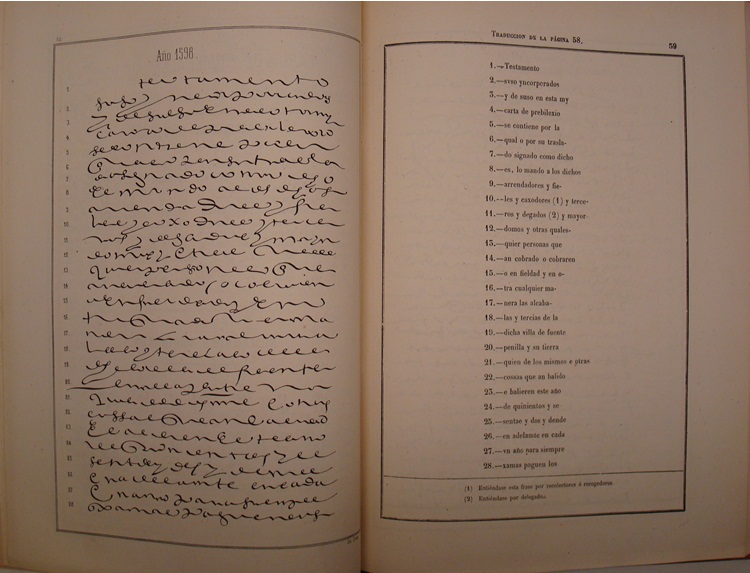
La Historia de la Paleografía en el s. XIX está directamente marcada por la gran obra de finales del XVIII del P. Merino:
"ESCUELA PALEOGRAPHICA ó DE LEER LETRAS ANTIGUAS". (
Madrid: Juan Antonio Lozano, 1780) y la mayoría de autores hacen referencia directa a ella reproduciéndola en sus tratados. Estas obras, junto con la paleografía de Palucie y Cantalozella y las diferentes obras de Muñoz y Rivero de finales del XIX de las cuales ya hemos hablado anteriormente, son las más importantes publicadas en el s XIX en España sobre la materia.
En general todas las obras citadas ayudaron a generalizar y difundir la paleografía en las escuelas de estudios superiores y su edición más utilitaria que lujosa demuestra el cambio en la accesibilidad a la educación de mayor número de alumnos y estudiosos de la paleografía en el s XIX que en anteriores épocas.
Referente al contenido estricto de su validez actual, algunos paleógrafos como C. A. Millares no dan mucha importancia académica, sinó la meramente bibliográfica y histórica a estas obras, excepto a las de Muñoz y Rivero.
ALVERÁ Y DELGRÁS, ANTONIO, "COMPENDIO DE PALEOGRAFÍA ESPAÑOLA ó ESCUELA DE LEER TODAS LAS LETRAS QUE SE HAN USADO EN ESPAÑA DESDE LOS TIEMPOS MÁS REMOTOS HASTA FINES DEL SIGLO XVIII". Madrid: Imprenta de D. Anselmo Santa Coloma, 1857. Folio. 30 páginas de texto, 32 láminas, y VIII páginas más de aditamento, para transcripción en impreso del texto.
Cito una vez más a Cotarelo y Mori, (*) nº 44: " Los ocho láminas primeras están copiadas de la "Paleografía Primitiva" del P. Bernard, impresa en París en 1689, las ocho siguientes son de la Paleografía de D. Cristhoval Rodríguez y de la Escuela de leer del P. Merino: de este nueve textos y dos de Rodríguez: otros cuatro son de Alverá"....." El texto contiene multitud de noticias curiosas , pero que no se relacionan inmediatamente con la paleografía, faltando una indicación metódica de los caracteres distintivos de cada clase de escritura, según las épocas"
El autor fué un notable calígrafo casi al mismo nivel que Iturzaeta y escribió multitud de obras de caligrafía y también muchas para la educación os animo que veáis estas enteras on-line:
Compendio de Paleografía. Alverá y Delgrás. A.
Nuevo arte de aprender y enseñar a escribir la letra española para uso de todas las escuelas del Reino
(*) COTARELO Y MORI, EMILIO. "DICCIONARIO BIOGRÁFICO Y BIBLIOGRÁFICO DE LOS CALÍGRAFOS ESPAÑOLES. Madrid, 2004, Visor Libros, (reimpresión facsímil de la edición de 1916)
GONZALO DE LAS
CASAS, JOSÉ. "ANALES DE LA PALEOGRAFÍA ESPAÑOLA compilados y ordenados por.." Madrid: Establecimiento Literario del Centro del
Notariado, 1857.
Cuarto, hoja con portadilla, hoja con el título en color, retrato del autor, portada, una serie de páginas numeradas en romanos des del VIII al XIV , 706 páginas que incluyen 151 láminas numeradas, una lámina final titulada: " Cuadro sinóptico general de los abecedarios paleográficos"
Publicada en entregas a suscriptores esta paleografía completa es de difícil adquisición, la mayoría de ejemplares que hemos visto carecen de alguna que otra página o del retrato del autor, (el ejemplar en linea carece del retrato)
Esta obra esta basada en paleografías españolas anteriores y en algunos autores extranjeros. Reproduciremos también la versión en cuadernillos que era de la forma en que se distribuyó originalmente.
Primer formato de venta por entregas a subscriptores,
cada entrega se componía de unos capítulos de texto con sus láminas |
MORIANO, FELIPE. "ARTE DE LEER LOS IMPRESOS ANTIGUOS CASTELLANOS"
Sevilla: Antonio Izquierdo, 1861. Octavo, Tapa en azul. portadilla y portada, las tres con título. prólogo numerado en números romanos de III páginas, 276 páginas más una hoja de erratas, un folio en blanco y tapa final.
Este libro tal como dice el título es indicado y utilísimo para leer el castellano antiguo impreso, ya que analiza con toda profundidad las formas gramaticales y de abreviación que existían en los textos antiguos. La procedencia de algunas letras como la "Ñ" las variantes de escritura en algunos textos, los verbos etc... los números, etc...toda una fuente de información. Para todos los que tengan interés filológico sobre castellano antiguo resulta imprescindible.
(*) COTARELO Y MORI, EMILIO. "DICCIONARIO BIOGRÁFICO Y BIBLIOGRÁFICO DE LOS CALÍGRAFOS ESPAÑOLES. Madrid, 2004, Visor Libros, (reimpresión facsímil de la edición de 1916)